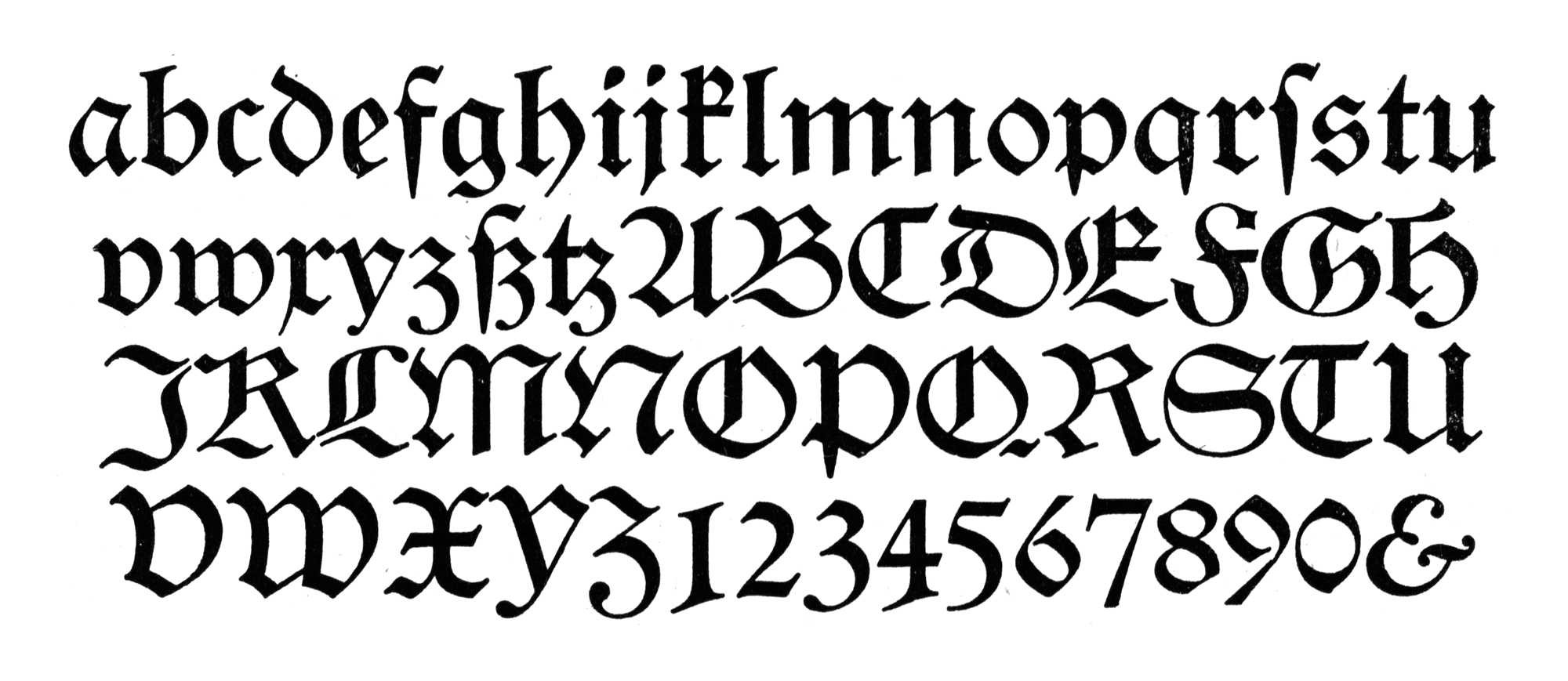
- 1914
- Gebrochene Schrift
Die Schwabacherschrift Renata erschien 1914 bei der Schriftgießerei Flinsch und später bei der Bauerschen Gießerei.
Eine Digitalisierung gibt es von Gerhard Helzel.